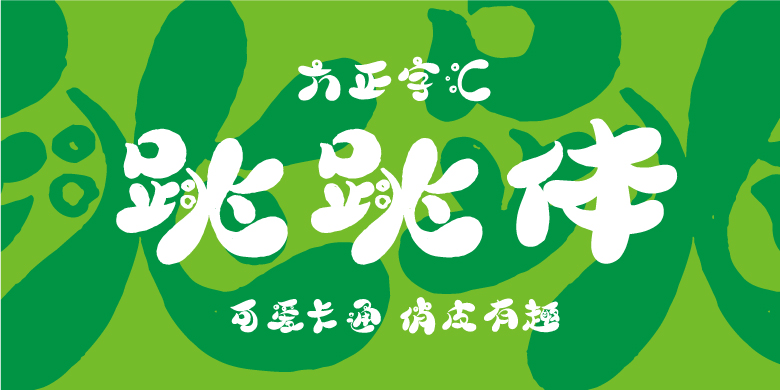
方正字汇-跳跳体
字体品牌: 方正字汇 设计师:杨伟 字体分类:创意字体 字体属性:精品字 字符集:大陆简体(GB2312-80) 发布时间: 2024
生命似汪洋大海,我们在这惊涛骇浪里生长,热情、奔腾、流动、这套字体也融入了水的善万物而又不争的包容姿态,线条圆润活泼似一群在大海中徜徉的精灵,结构伸展自如张弛有度,造型稚趣,灵动的点似这汪洋大海中呼吸的浪花-自由欢快,生命本该如此多姿。